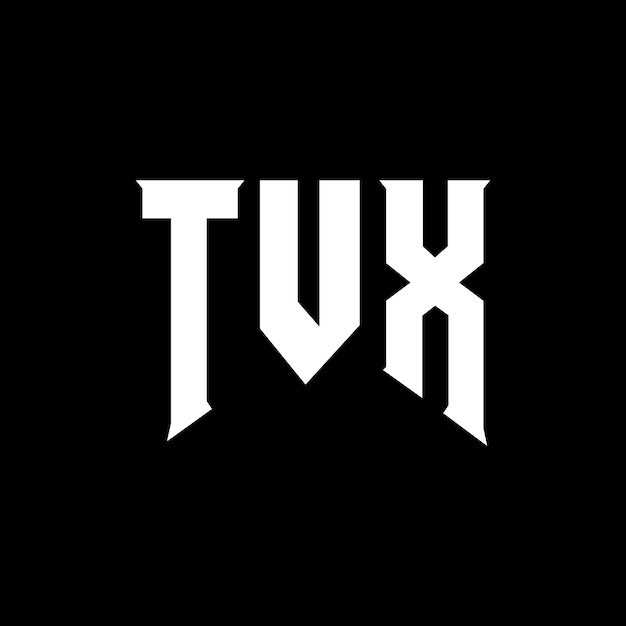
Design de logo de lettre TUX pour l'entreprise de technologie Design de logo TUX combinaison de couleurs noir et blanc Logo TUX vecteur TUX design Icône TUX alphabet TUX typographie Design de logo